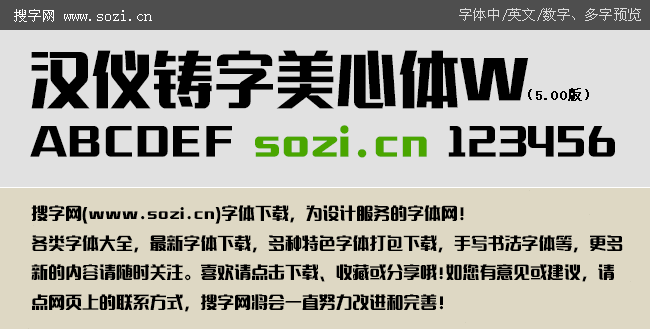
漢儀鑄字美心體W
搜字網(wǎng)提供一款漢儀鑄字美心體W中文字體下載,漢儀鑄字美心體秀美之余不失正氣,結(jié)構(gòu)嚴(yán)謹(jǐn),線條粗壯有力,字形端正大方得體,適合應(yīng)用于廣告設(shè)計(jì)、名片設(shè)計(jì)、包裝印刷、產(chǎn)品設(shè)計(jì)等應(yīng)用。